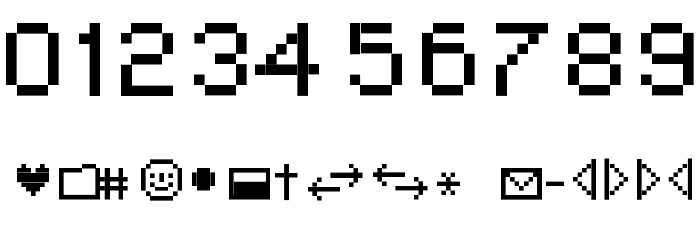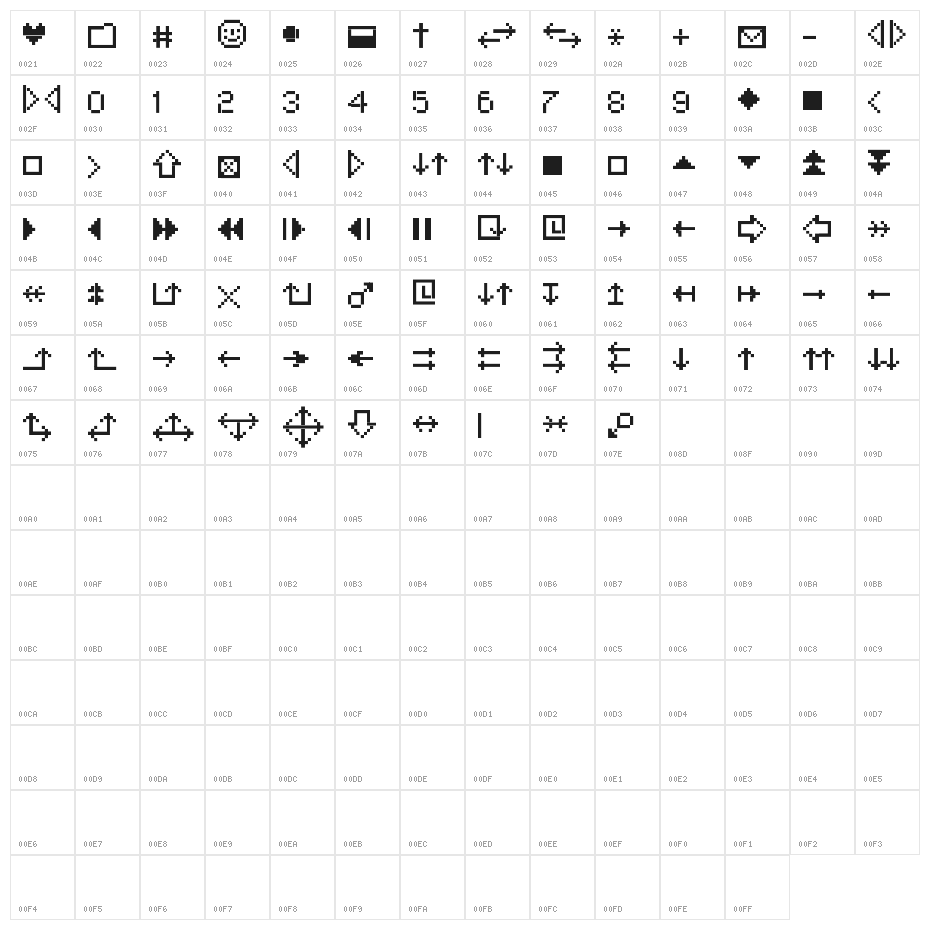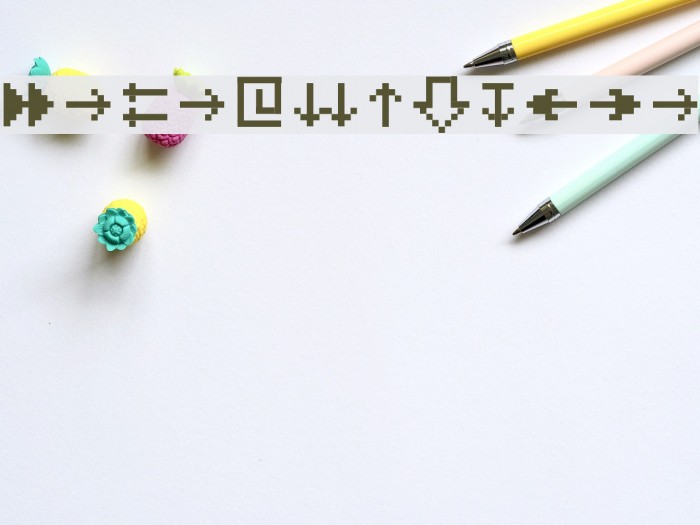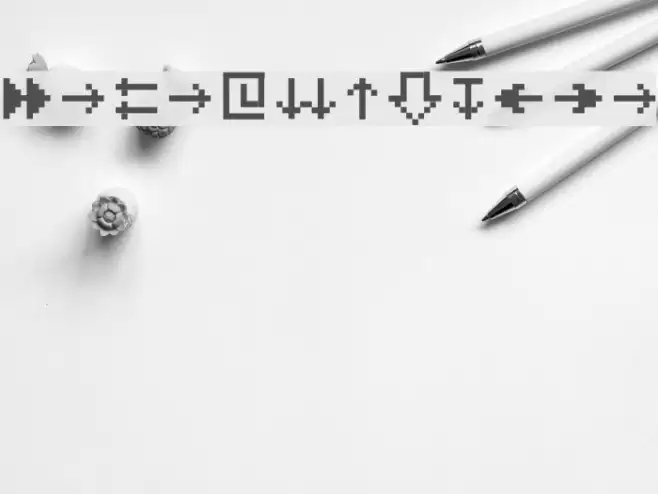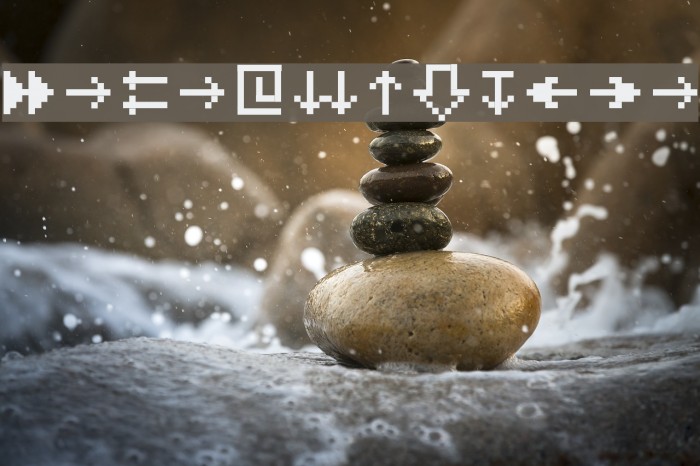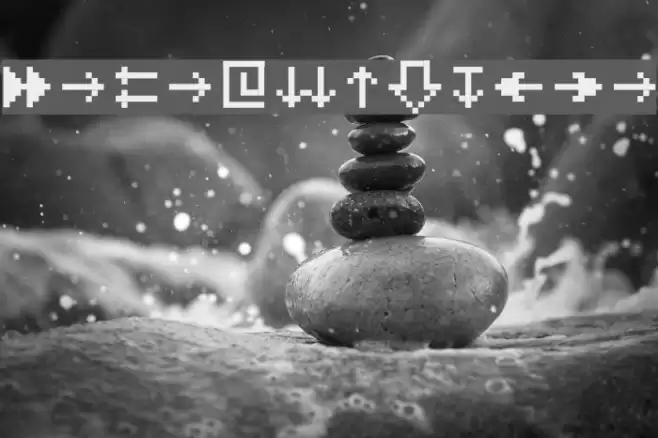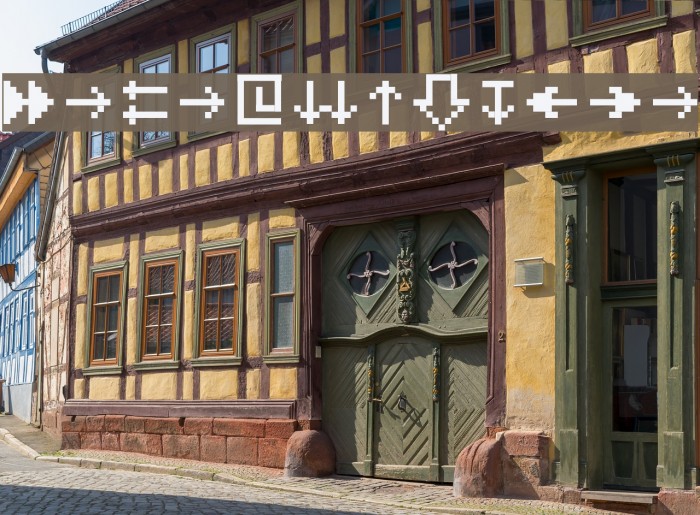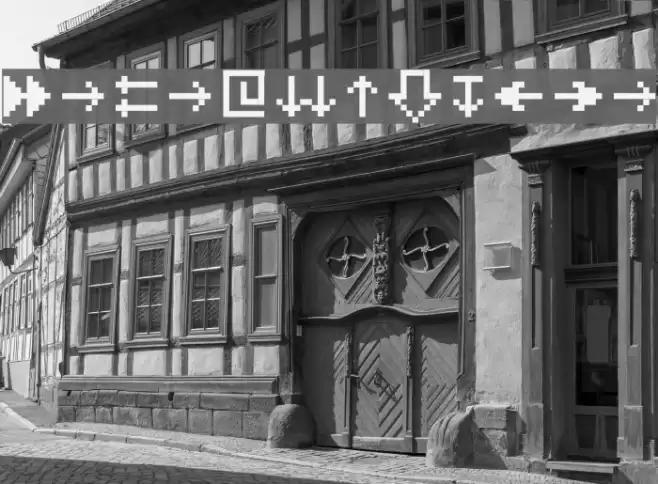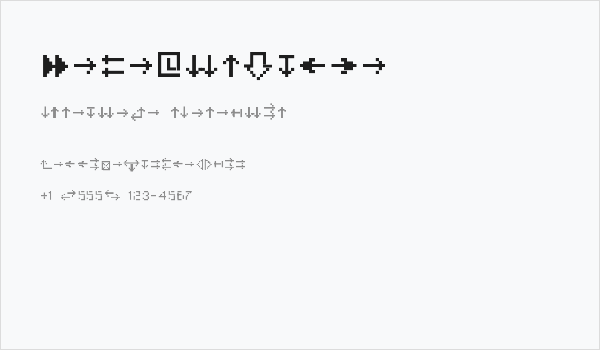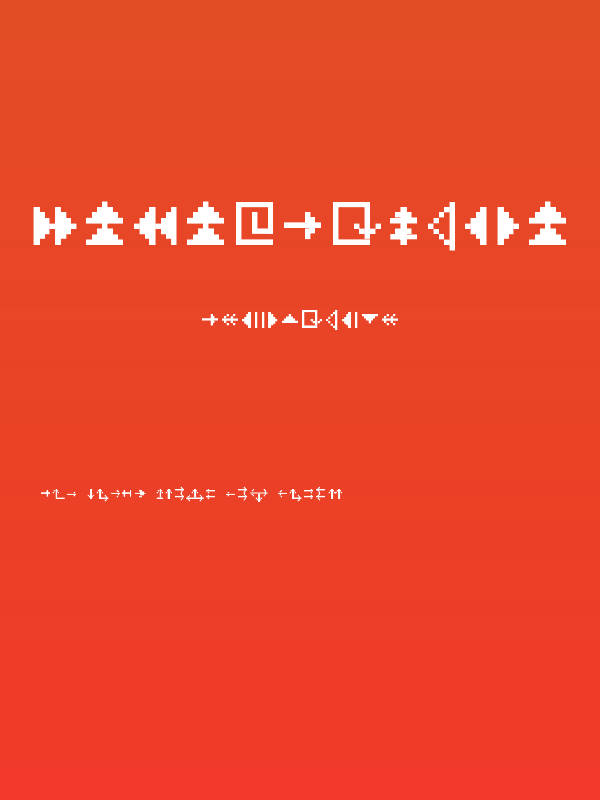
MiniStrzalki Font
| Style général | Retro, Digital |
| Cas d'utilisation | Logos, Digital Art, Video Game Interfaces |
| Projets proposés | Ideal for retro-themed designs, digital art projects, video game interfaces, and any creative work requiring a nostalgic, pixelated aesthetic. |